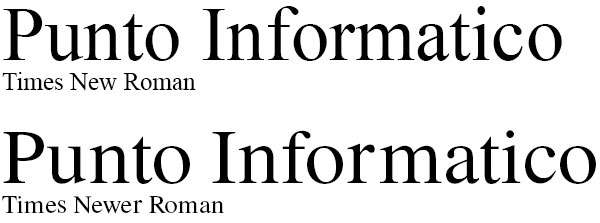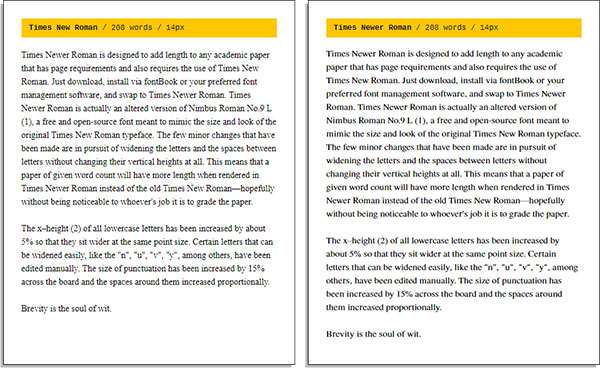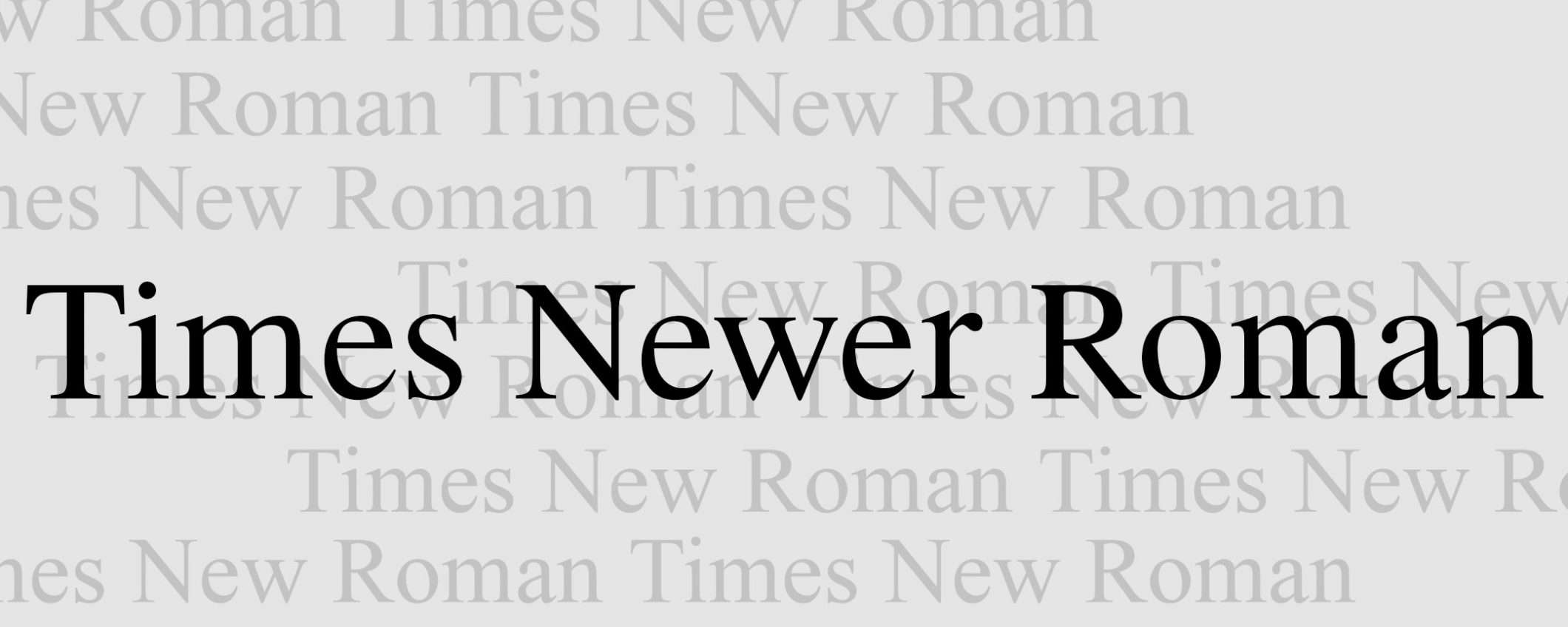
Non si tratta di un refuso, Times Newer Roman è il nome del font disegnato e distribuito da MSCHF, crogiolo di idee originali e progetti bizzarri legati al Web. Parente stretto della più nota alternativa ufficiale, ne riprende lo stile, ma incrementando la larghezza dei singoli caratteri in modo difficilmente apprezzabile a uno sguardo non esperto: il risultato è un testo che occupa più spazio rispetto all’equivalente scritto in Times New Roman.
Times Newer Roman
Il font è offerto in download gratuito e può essere installato su qualsiasi computer, così da utilizzarlo nell’elaborazione dei testi. Si stia però attenti alla fase di esportazione: se l’obiettivo è la stampa o l’invio di un PDF nessun problema, in caso contrario difficilmente il destinatario disporrà del carattere e finirà per visualizzare il file in modo differente da come è stato concepito. Stando a quanto dichiarano i creatori, per completare un documento standard di 15 pagine, senza alterare spaziatura, corpo o interlinea, servono 5.833 parole anziché 6.680. Per capire cosa cambia è sufficiente dare un’occhiata all’immagine seguente.
La creazione del Times Newer Roman si basa sull’elaborazione del Nimbus Roman No. 9 L, carattere nato negli anni ’80 proprio per emulare l’aspetto del Times New Roman e oggi font predefinito di numerose distribuzioni Linux, liberamente modificabile grazie alla sua natura free e open. Questo perché il più celebre Times New Roman è invece offerto in licenza dalla Monotype Corporation.
Di seguito un esempio concreto: lo stesso testo composto da 208 parole scritto con corpo carattere 14, a sinistra in Times New Roman e a destra in Times Newer Roman. Nel secondo caso si arriva a occupare l’intera pagina in altezza.
Times New Roman, le origini
Il Times New Roman è uno dei caratteri tipografici più noti e utilizzati di ogni tempo. Le sue origini risalgono addirittura agli anni ’30 del secolo scorso, ad opera dell’incisore Stanley Morison e del designer Victor Lardent. Si ha testimonianza del primo impiego sul quotidiano britannico The Times stampato il 3 ottobre 1932. I suoi ideatori lo immaginarono come un carattere facilmente leggibile e caratterizzato da un occhio medio stretto ovvero maggiormente sviluppato in altezza piuttosto che in larghezza, così da semplificare il posizionamento dei testi all’interno delle colonne del giornale. Si può dunque affermare che il suo successore illegittimo, il Times Newer Roman, vada in qualche modo a tradire la sua natura.